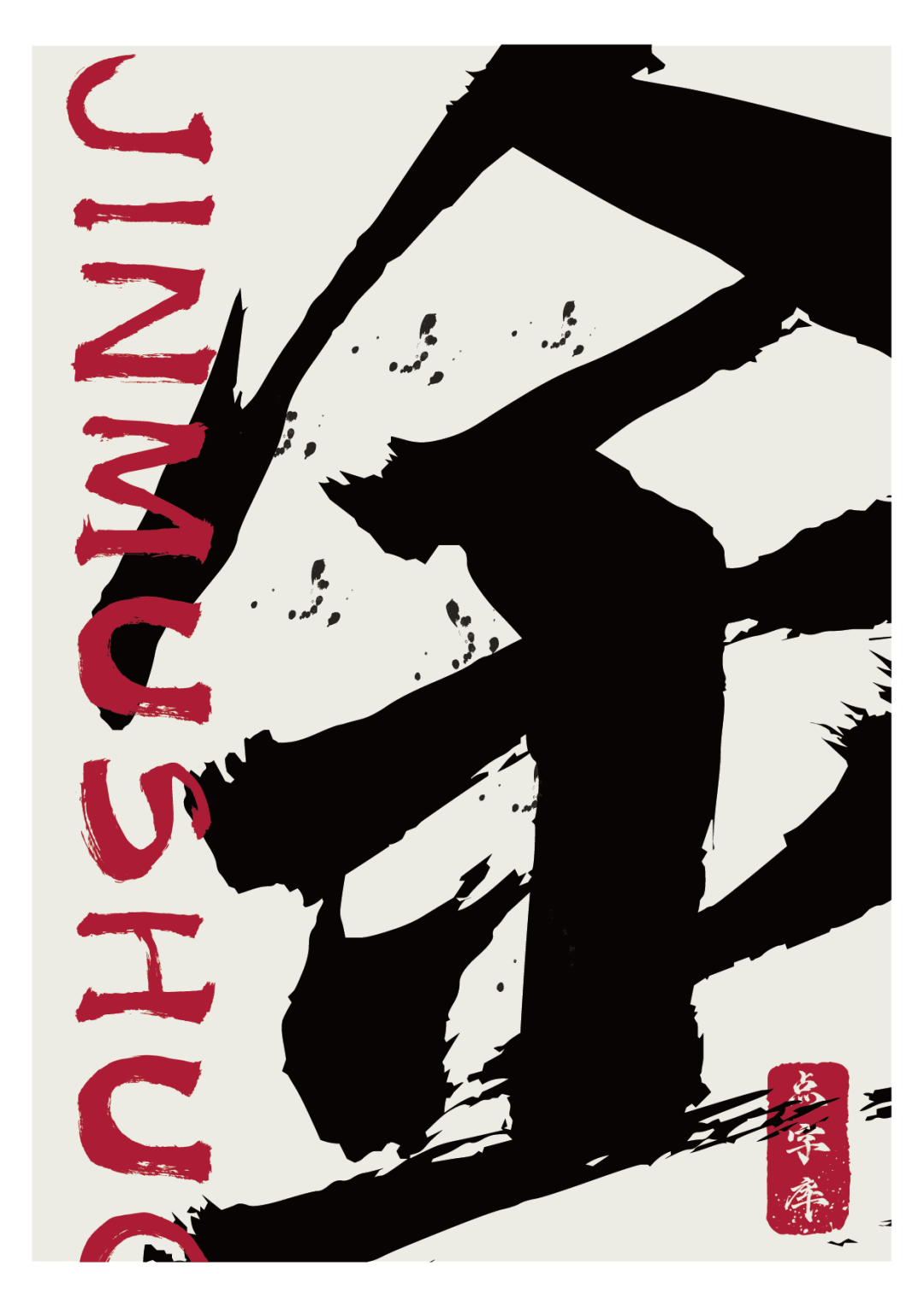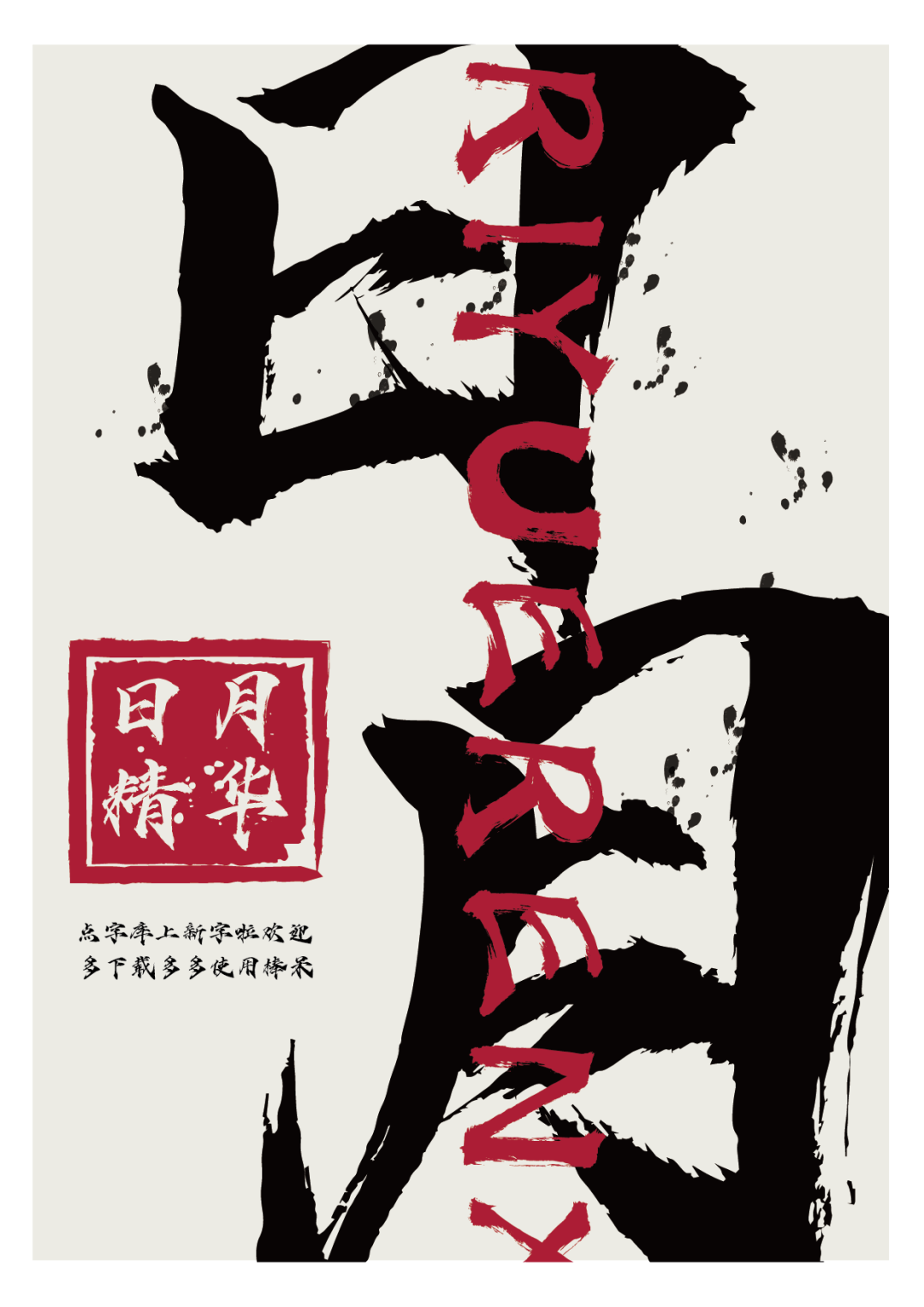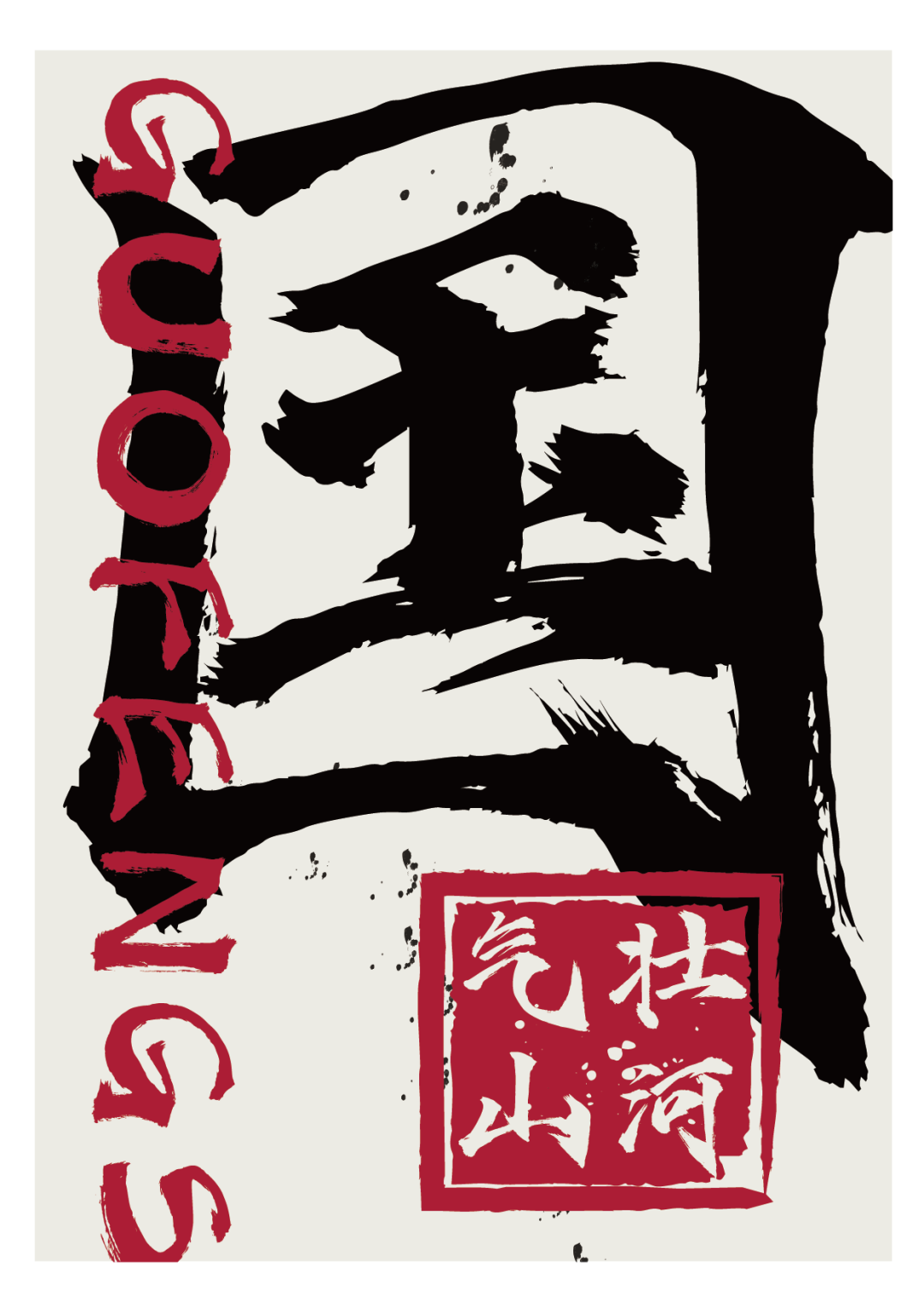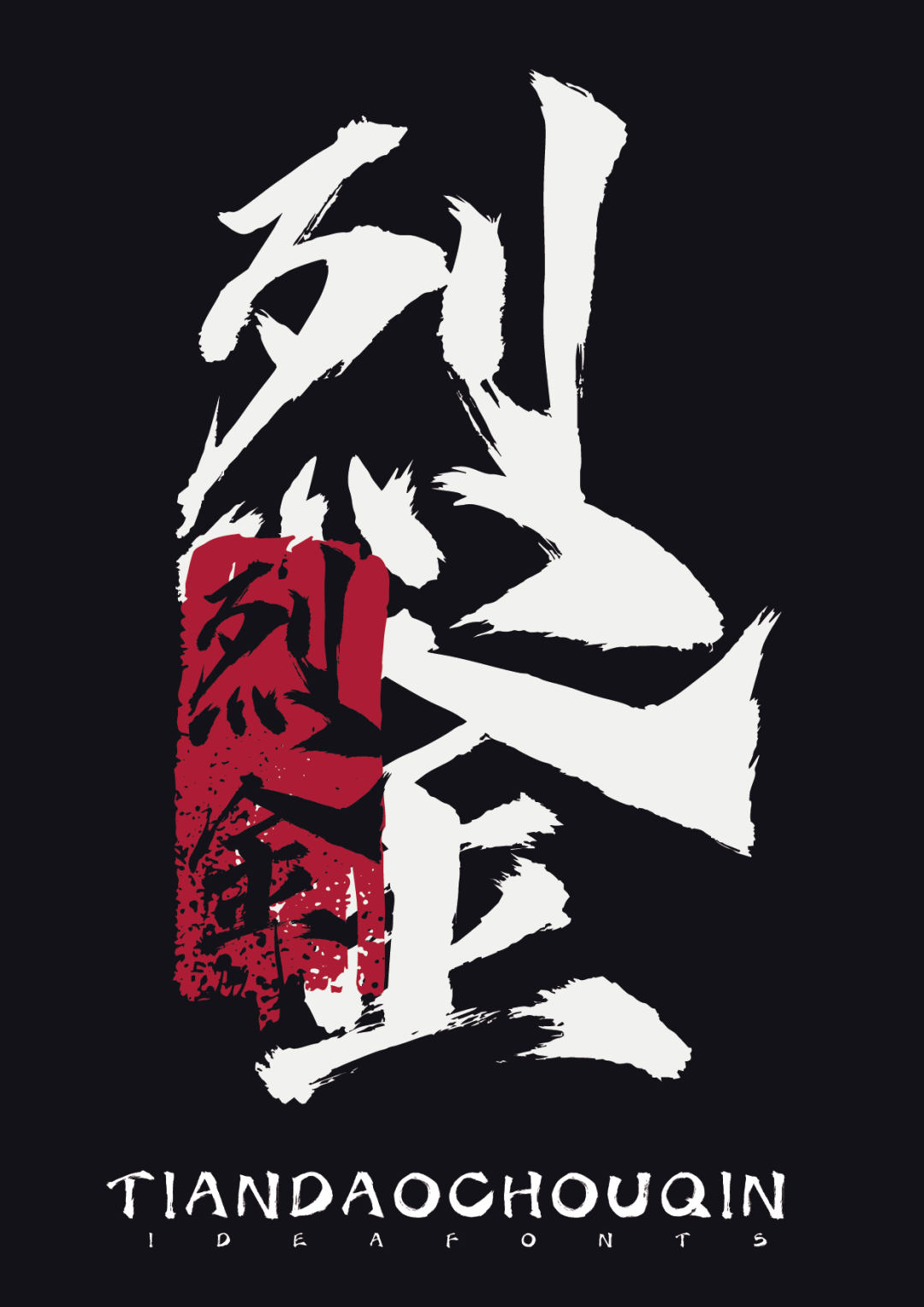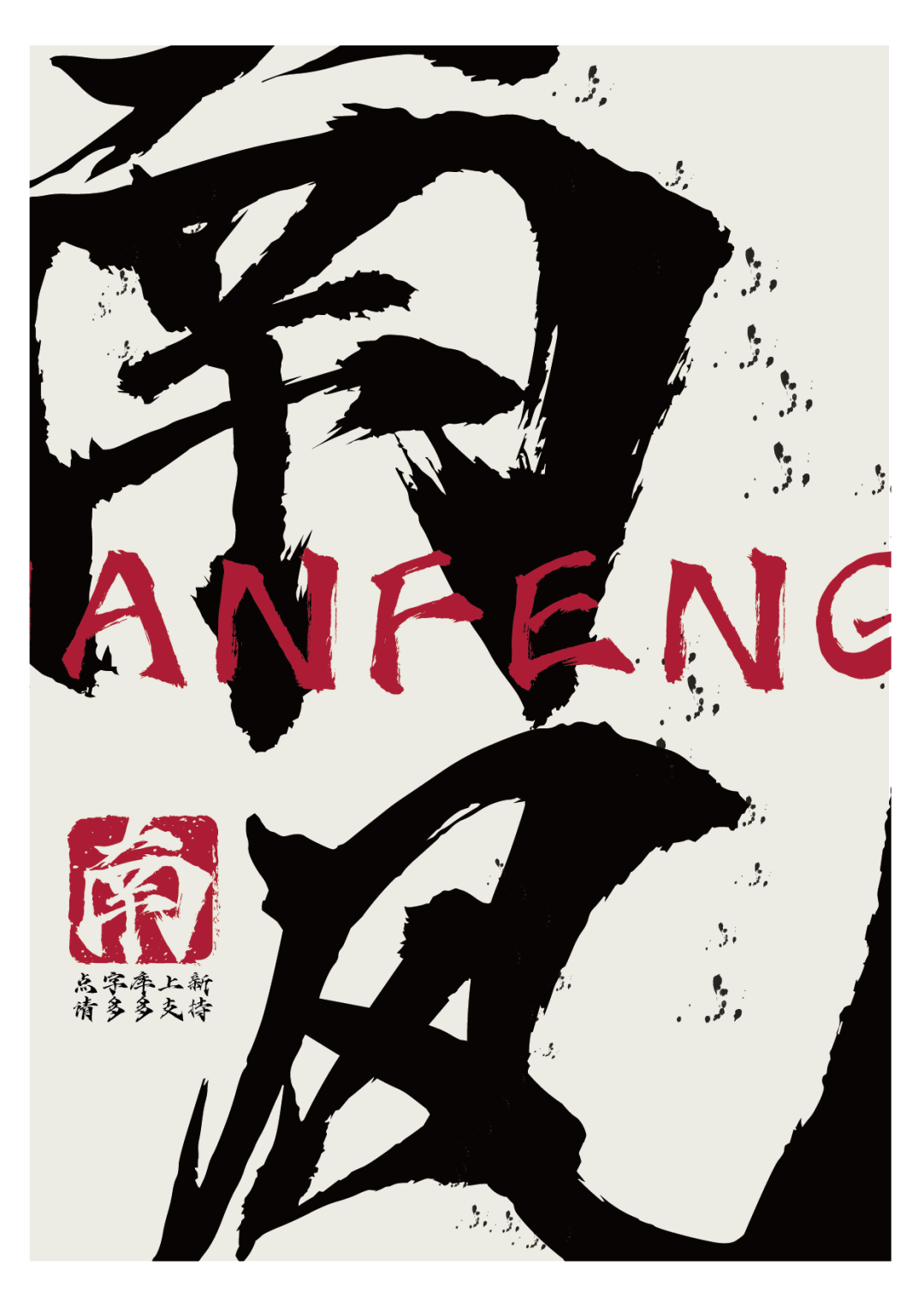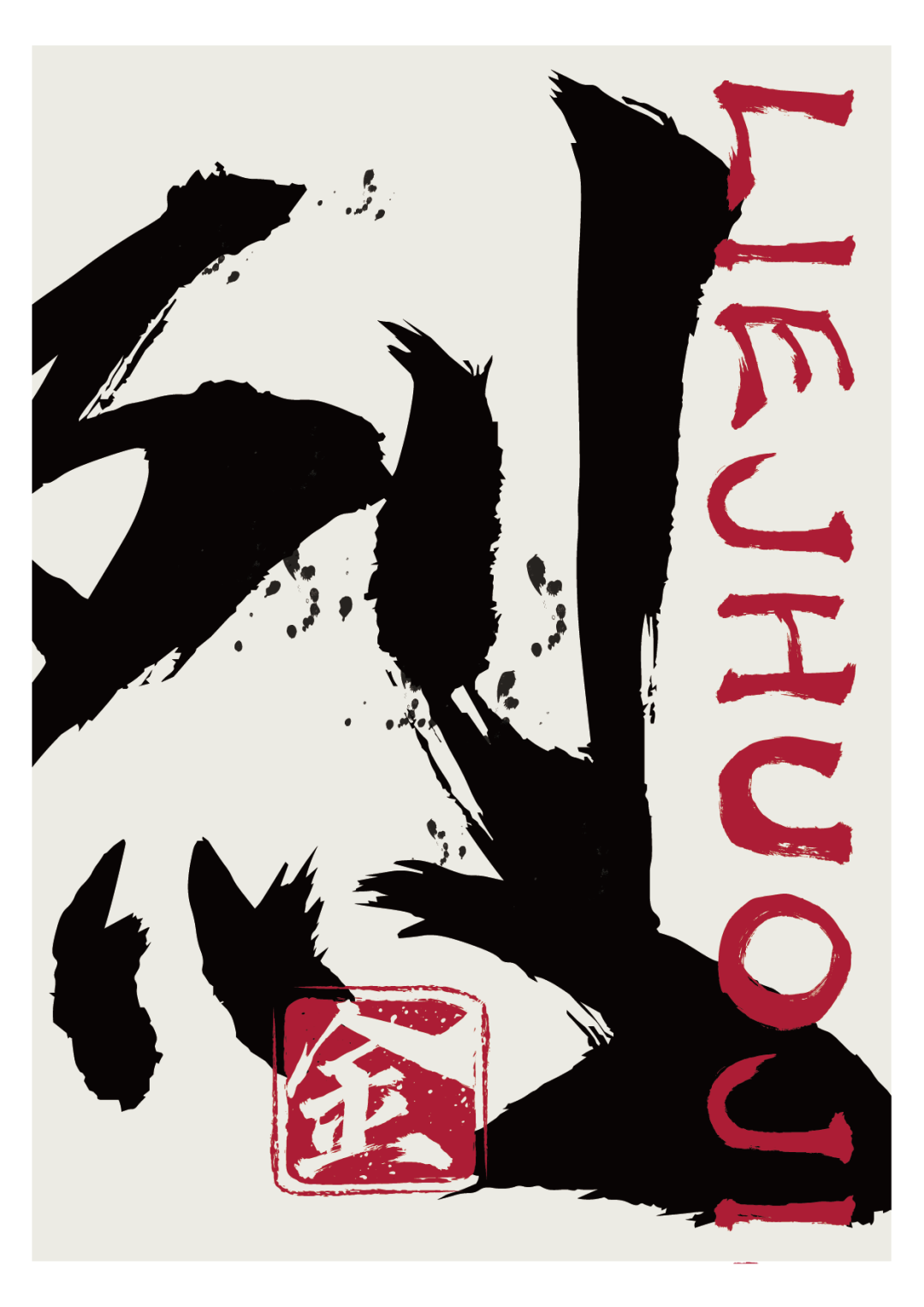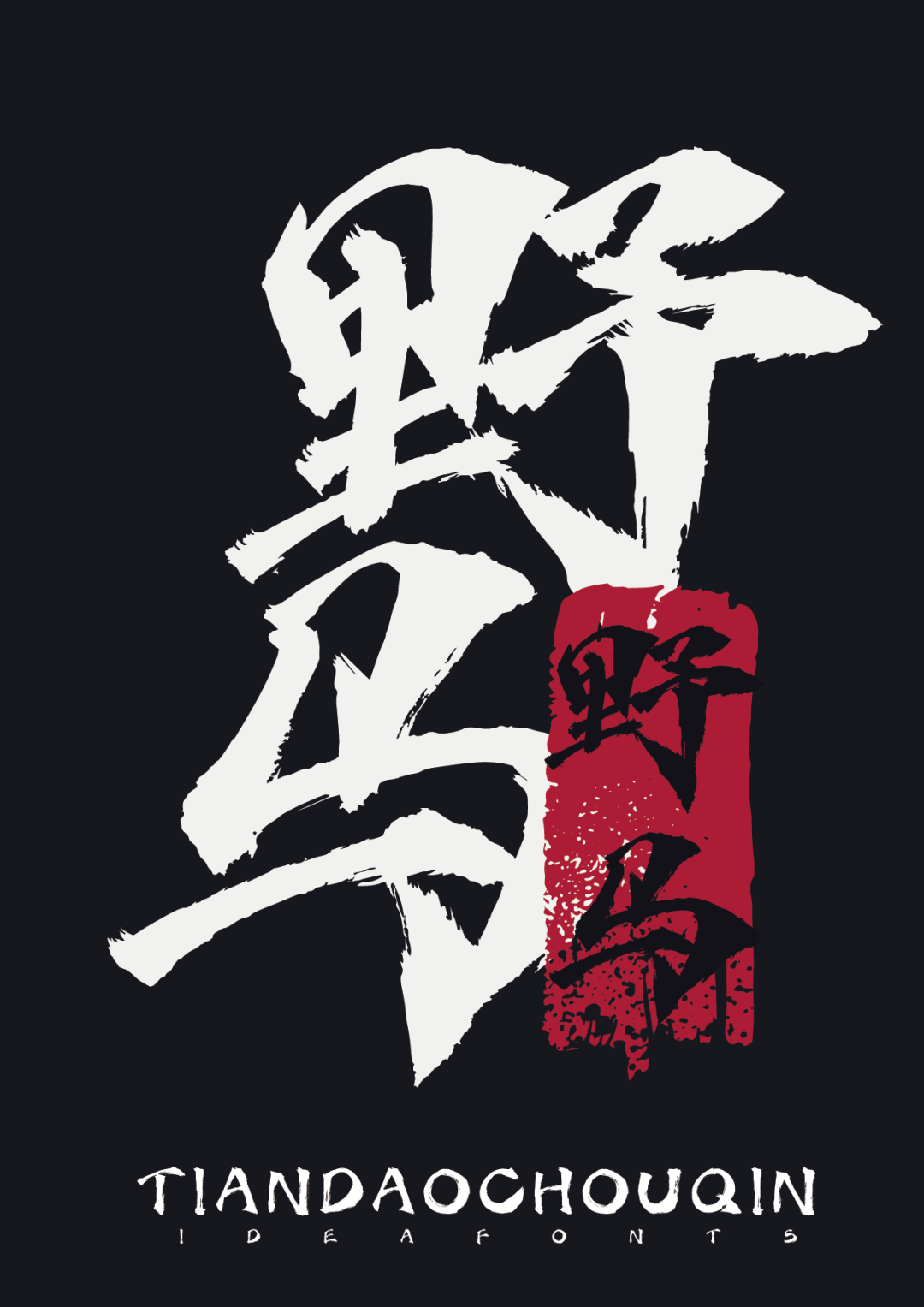
点字烈金体介绍,一款美强惨的字体
自从字由会员上了一波手写体后,就受到了广大用户的疯狂安利~
颜值爆表也就算了,最关键的是每种字体,都“帅”得不一样!
那场面就好比看到了琉璃男团……
你细品这画风,字体和人物还挺匹配,中间的C位也出现了!
那哪款字体,才能配得上我们意气风发、霸气魔尊、深情款款的司凤呢?悬念揭晓~
全剧不是在吐血,就是在吐血的路上, 实为(惨)烈!
还拥有一双羡煞旁人的大金翅和金甲战袍,实在很A!
最关键的是,十赌九输的深情,将万千少女成功洗脑……
那这么美强惨的字体,用在设计中是什么样呢?看看它的细节~